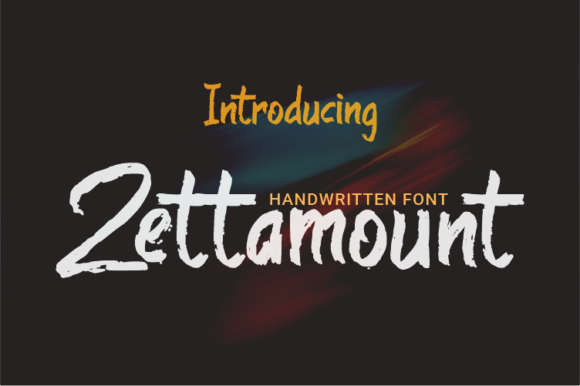
Zettamount - это классный, отшлифованный рукописный шрифт, отличающийся идеальной модностью.
Неважно, используете ли вы его для рукоделия, цифрового дизайна, презентаций или поздравительных открыток - он идеален!